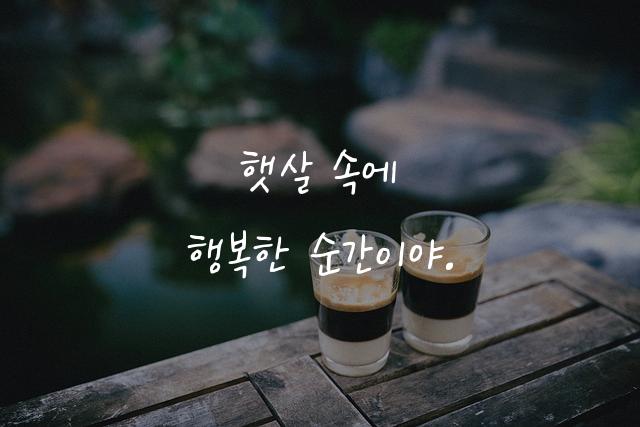
온글잎 매일옥자체는 강주윤과 온글잎이 협업하여 만든 삐뚤빼뚤한 감성이 돋보이는 폰트입니다. 이 폰트는 일상적인 글씨체와는 다른, 특별하고 개성 넘치는 느낌을 제공합니다.
온글잎 매일옥자체은(는)
계열의 생김새를 가지고 있으며
교육 자료, 어린이 책, 일기/편지 등에서 자주 활용되며, 효과적인 메시지 전달에 적합합니다.
이 폰트는 교육, 출판/미디어, 유아/가족 분야에 잘 어울리며,
친근한, 부드러운, 편안한 느낌을 담고 있는 것이 특징입니다.